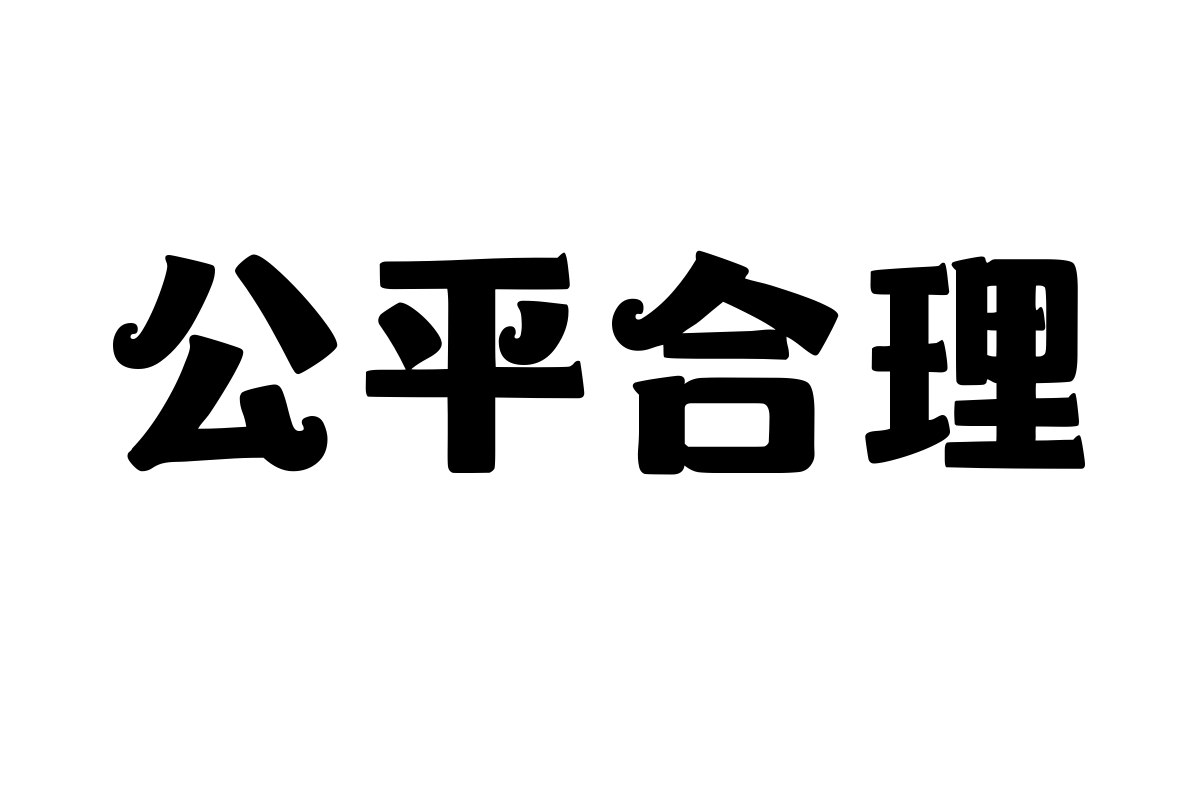
**山海童话物语W是一款具有独特美感和实用性的中文字体,适合用于艺术设计、平面宣传设计和网页设计等领域**。
山海童话物语W字体以其独特的风格和优雅的设计,在众多字体中脱颖而出。该字体家族名称为“ShanHaiTongHuaWuYu W”,样式名称为“Regular”,共有9915个字符。这种字体的特点在于其适中的笔触和端正的字形,使其在视觉上呈现出很好的效果,适合应用于需要清晰易读的场合。
山海童话物语w